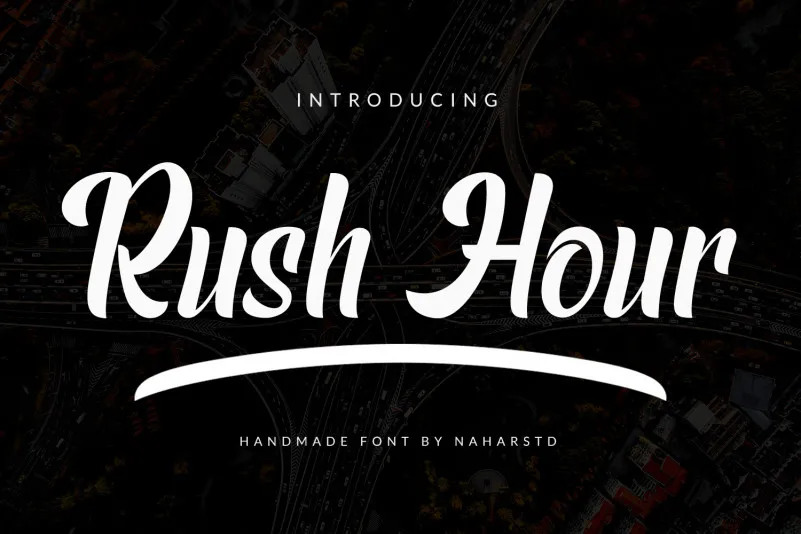
Rush Hour Script Font – Download Grátis
Rush Hour Script Font é uma escolha ideal para qualquer projeto que exige expressividade moderna e linhas suaves. Este font se destaca não apenas pela sua aparência sóbria, mas também por seu uso de curvas elegantes. Ideal tanto para design de logotipos quanto para criação de letras artísticas, essa font é uma ótima opção para quem procura expressar identidades visuais com modernidade e sofisticação. Seja em uma capa de livro ou mesmo em camisetas esportivas, esse Rush Hour Script Font garante um visual atraente e único. Se você está buscando algo que destaque seu design em qualquer mídia visual, não hesite em usar o Rush Hour Script Font. Suas linhas finas e suaves combinam perfeitamente com letras amplas e criativas, tornando-se uma fonte versátil para um amplo espectro de projetos, como revistas, materiais de embalagem, materiais publicitários, camisas de desportivo e até mesmo capas de livros. Com essa fonte, você pode criar mensagens que chamem a atenção em qualquer evento especial ou projeto design. E se for para criar uma identidade visual sólida e moderna para sua marca, isso é um passo à frente.
Designer: Naharstd